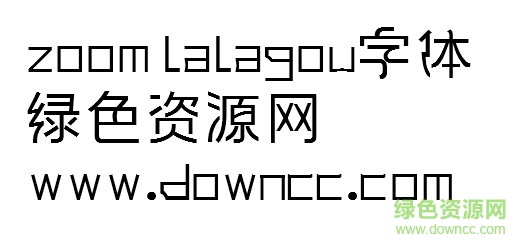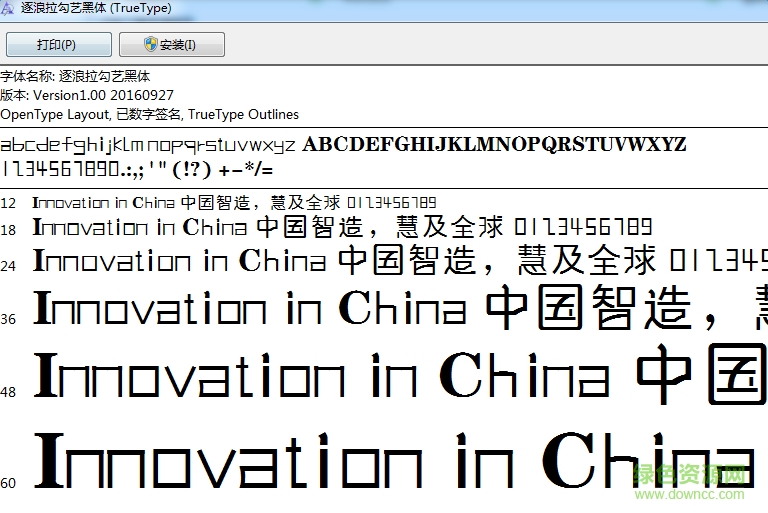
zoomlalagou ao12是逐浪拉勾藝黑體的英文名稱,本字體造型迥異,是一款書寫優(yōu)雅、藝術(shù)感豐富的海報(bào)字體,同時(shí)黑體的特色讓字體給人印象深刻,一起來綠色資源網(wǎng)體驗(yàn)吧!
zoomla字體線條粗細(xì)適中,字形飄逸大方得體,整體效果非常的出色,可廣泛應(yīng)用于平面設(shè)計(jì)、廣告設(shè)計(jì)、報(bào)紙雜志、正文標(biāo)題等領(lǐng)域。